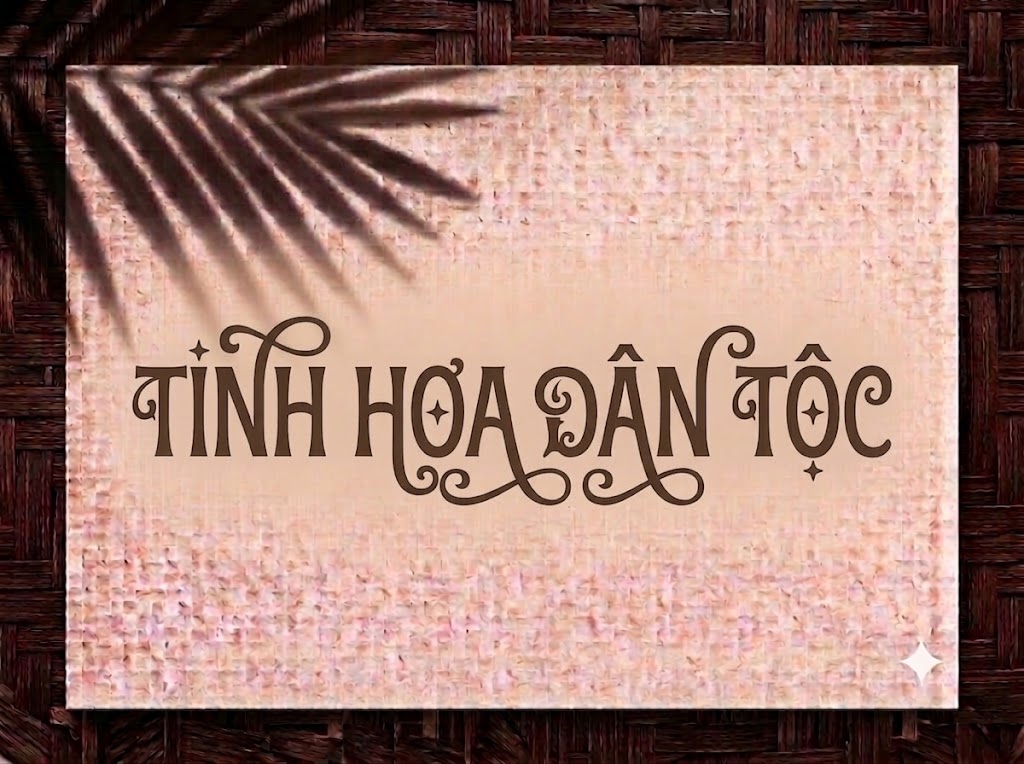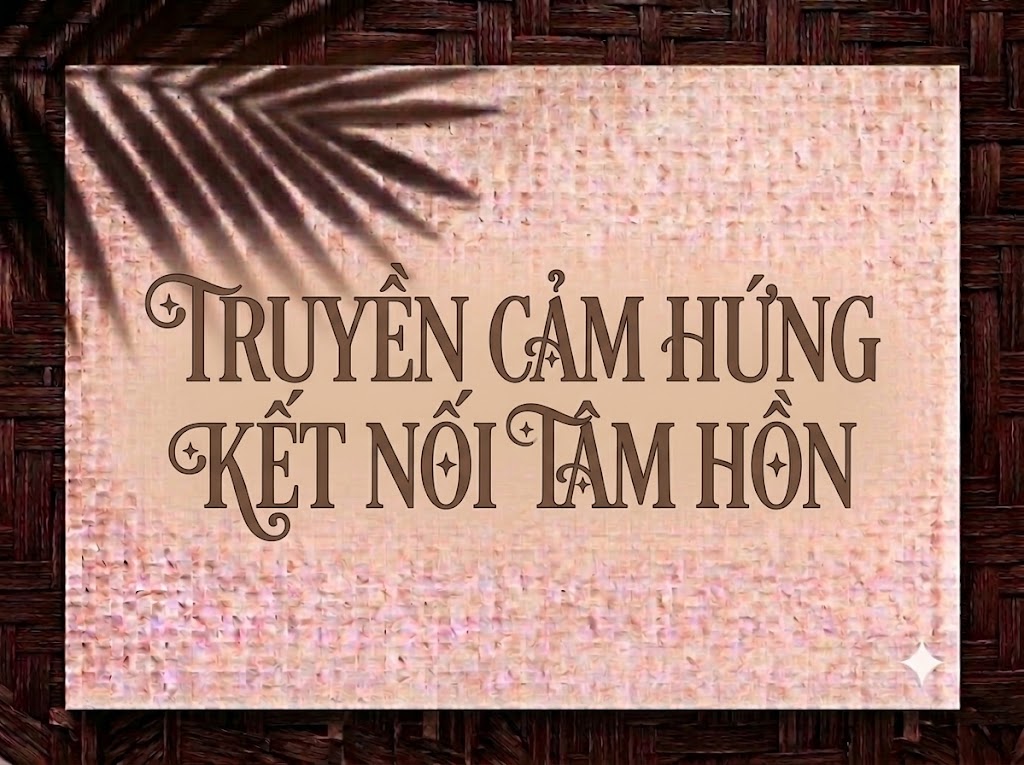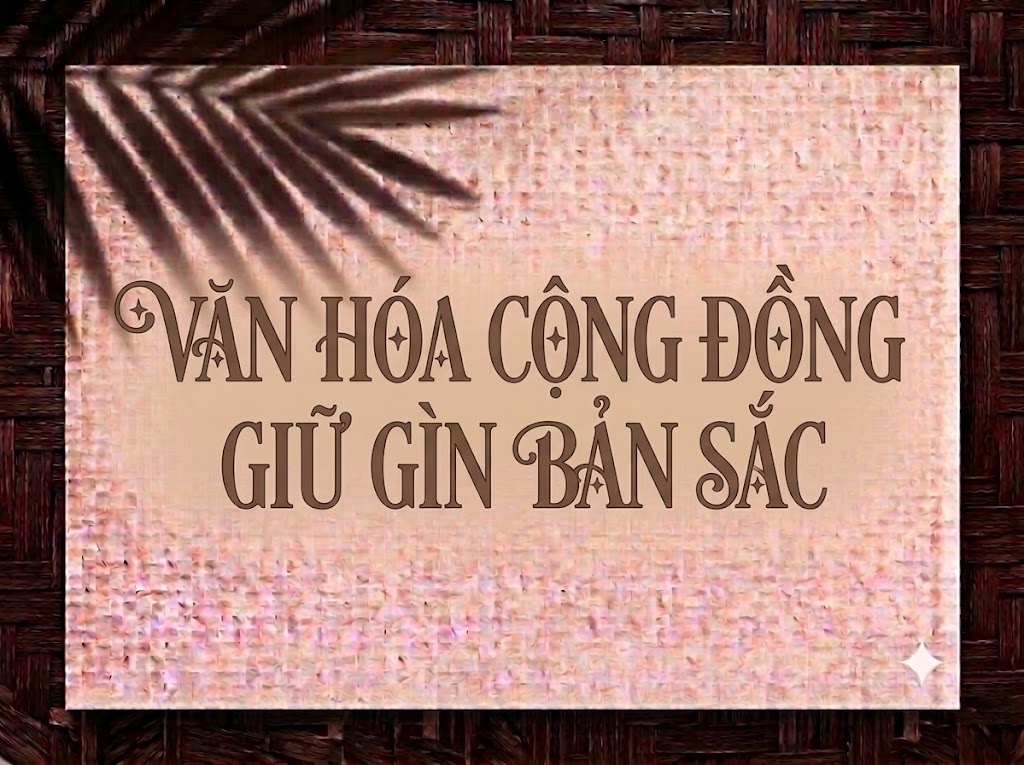
1FTV Psychoart
Trong thế giới thiết kế đồ họa cá tính, bên cạnh các dòng phông chữ Sans-Serif tối giản hay Serif sang trọng, những bộ chữ mang phong cách Psychedelic (nghệ thuật ảo giác) kết hợp hơi hướng Art Nouveau luôn có một chỗ đứng rất riêng. Chúng sinh ra để tạo nên tác động thị giác mạnh mẽ, khơi gợi trí tưởng tượng và định hình phong cách độc bản cho các ấn phẩm mang tính nghệ thuật cao.
Nếu bạn đang tìm kiếm một phông chữ hiển thị ma mị, uốn lượn đầy cảm xúc để làm bìa album nhạc, poster triển lãm hay tiêu đề video ngắn, font 1FTV Psychoart chính là sự lựa chọn không thể bỏ qua.
Giới thiệu về font 1FTV Psychoart
Font 1FTV Psychoart là bộ chữ hiển thị trang trí (display font) sở hữu phong cách thiết kế tự do, uốn lượn kết hợp giữa nét cổ điển và tinh thần phá cách hiện đại:
Tên phông chữ: 1FTV Psychoart
Thông số kỹ thuật: Định dạng OpenType Layout, tích hợp chữ ký kỹ thuật số (Digitally Signed) và hệ thống đường nét PostScript Outlines chuẩn xác.
Được hoàn thiện kỹ lưỡng trên công cụ biên dịch phông chữ chuyên nghiệp, 1FTV Psychoart mang lại khả năng hiển thị vô cùng sắc nét. Bạn có thể tự tin phóng lớn chữ trên các phần mềm đồ họa hay ứng dụng dựng phim mà không lo gặp tình trạng vỡ nét hay răng cưa.
Đặc điểm nổi bật của phong cách thiết kế Psychoart
Sức hút thị giác của font 1FTV Psychoart đến từ vẻ đẹp uốn lượn ma mị cùng sự biến điệu ký tự đầy tính nghệ thuật:
Phong cách Psychedelic & Art Nouveau độc đáo: Những đường cong biến điệu mềm mại ở nét chữ gợi nhớ đến phong cách nghệ thuật ảo giác thập niên 60-70 kết hợp vẻ cổ điển quyến rũ.
Tạo hình ký tự phá cách: Điểm nhấn đắt giá của phông chữ nằm ở cấu trúc các ký tự như
T,h,k,q,x,g,e. Đầu chữTvươn nhẹ nghệ thuật, phần chân chữh,kuốn cong mở rộng cùng các nét nối mềm mại tạo nên tổng thể vừa bay bổng vừa ma mị. -
Hỗ trợ chữ hoa và chữ thường đồng bộ: Phông chữ tích hợp trọn bộ hệ thống chữ cái in hoa, in thường cùng dãy số từ 0-9 dáng đứng cá tính, cho phép các designer linh hoạt phối hợp tạo nên nhịp điệu tiêu đề ấn tượng.
Để phông chữ vận hành mượt mà trên cả hệ điều hành Windows lẫn macOS, phiên bản này đã được xử lý kỹ lưỡng về mặt thông số nội tại:
Khoảng cách giữa các chữ (kerning) và độ giãn dòng được tính toán chuẩn xác, giúp các đường nét uốn lượn khi đứng cạnh nhau không bị dính nét hay gây cảm giác rối mắt.
Tích hợp trọn vẹn bộ chữ cái hoa – thường, dãy chữ số 0-9 cùng hệ thống ký tự đặc biệt, dấu câu thông dụng.
Bản Việt hóa chuẩn chỉnh giúp bạn hoàn toàn yên tâm thiết kế các văn bản tiếng Việt có dấu mà không gặp lỗi nhảy font hay mất ký tự.
Hình ảnh demo thực tế của font 1FTV Psychoart
Khả năng hiển thị của phông chữ này được tối ưu rất tốt trên nhiều tỷ lệ kích thước khác nhau:
Kích thước nhỏ (12pt – 24pt): Cấu trúc nét chữ rành mạch giúp bộ chữ thường và dãy số vẫn hiển thị rõ ràng, nét mượt trên màn hình di động.
Kích thước lớn (36pt – 72pt): Đây là đất diễn lý tưởng nhất để 1FTV Psychoart phô diễn toàn bộ sự biến điệu nghệ thuật của các đường uốn ở chữ
T,h,x,g, tạo tác động thị giác mạnh mẽ cho các dòng tiêu đề chính.
Ứng dụng trong thiết kế đồ họa và làm video
Sở hữu nét cá tính ma mị và giàu cảm xúc, font 1FTV Psychoart mở ra không gian ứng dụng phong phú:
Video ngắn (TikTok, Reels, Shorts): Phông chữ dáng uốn lượn này hiển thị rất thu hút trên khung hình đứng tỷ lệ 9:16. Cực kỳ ăn nhập với các video vlog nghệ thuật, podcast tâm lý, nhạc Indie, Chill, Lofi hay nội dung huyền bí.
Ảnh thu nhỏ YouTube (Thumbnail): Lựa chọn tuyệt vời cho các kênh làm nội dung về âm nhạc, review phim, kể chuyện kinh dị hoặc nghệ thuật sáng tạo nhờ giao diện độc lạ, dễ gây tò mò.
Thiết kế Bìa Album nhạc & Poster sự kiện: Hoàn hảo cho các poster triển lãm mỹ thuật, bìa đĩa nhạc Indie/Hip-hop, sự kiện âm nhạc ngoài trời hay các chương trình nghệ thuật đương đại.
Nhận diện thương hiệu Streetwear: Thích hợp làm logo dạng chữ nghệ thuật, nhãn mác sản phẩm hoặc in ấn thiết kế artwork trên áo thun cho các thương hiệu thời trang cá tính.